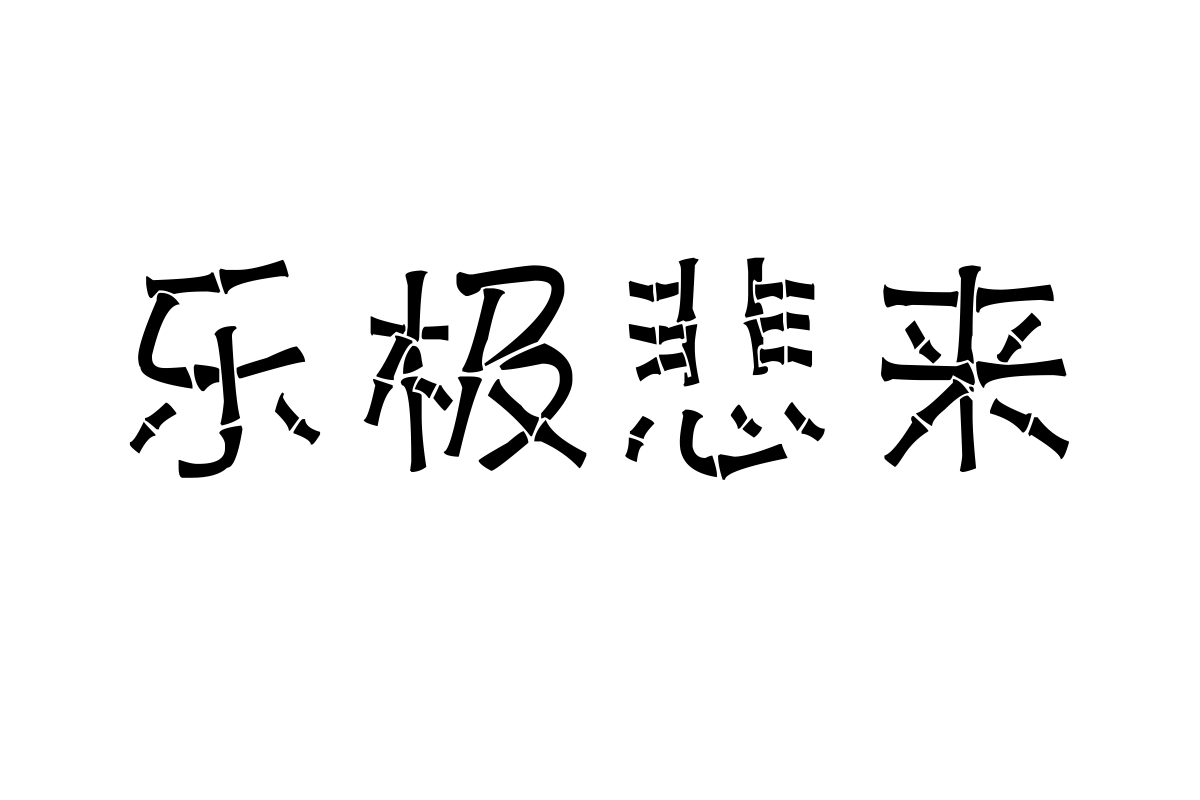
斑马竹节体是一种中文书法字体,由设计师陈幼坚设计。这种字体的特点是将传统的竹节形结构融入现代字体设计中,形成了独特的视觉效果。
斑马竹节体的特点是:
1. 线条流畅:斑马竹节体线条流畅,没有过多的装饰和修饰,给人一种简洁、大方的感觉。
2. 结构独特:斑马竹节体的每个笔画都像竹节一样,有粗细之分,使得整个字体看起来既有力量感,又不失柔美。
3. 易于识别:斑马竹节体的特点使得它在视觉上容易与其他字体区分开来,具有较高的辨识度。
4. 适用范围广泛:斑马竹节体适用于各种场合,如广告、宣传、包装等,具有很强的实用性。
总的来说,斑马竹节体是一种具有独特风格和广泛应用前景的中文书法字体。